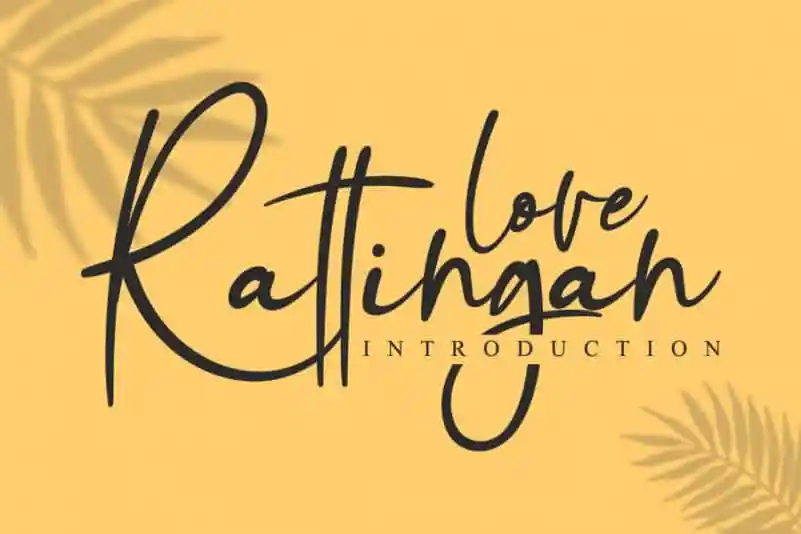
Rattingan Handwritten Font
A ‘Rattingan Handwritten Font’ é uma elegante escolha para qualquer designer que busca trazer um toque único e delicado aos seus projetos digitais. Essa fonte relaxada, mas ainda assim sofisticada, pode ser usada com sucesso em diversos contextos, desde pequenos detalhes de marca até elementos de design gráfico mais elaborados. Ideal para quem procura uma fonte que combina elegância com frescor moderno, a ‘Rattingan Handwritten Font’ não apenas adicionará um toque pessoal e único aos seus projetos, mas também os deixará distantes do convencional. Seja você um designer de logotipos, criador de aplicativos móveis ou até mesmo um profissional gráfico em busca de uma fonte que se destaca na multidão, esta elegante opção handwritten é certamente a escolha perfeita. Sinta-se à vontade para explorar as possibilidades criativas desta fonte e veja como ela pode moldar suas futuras criações.